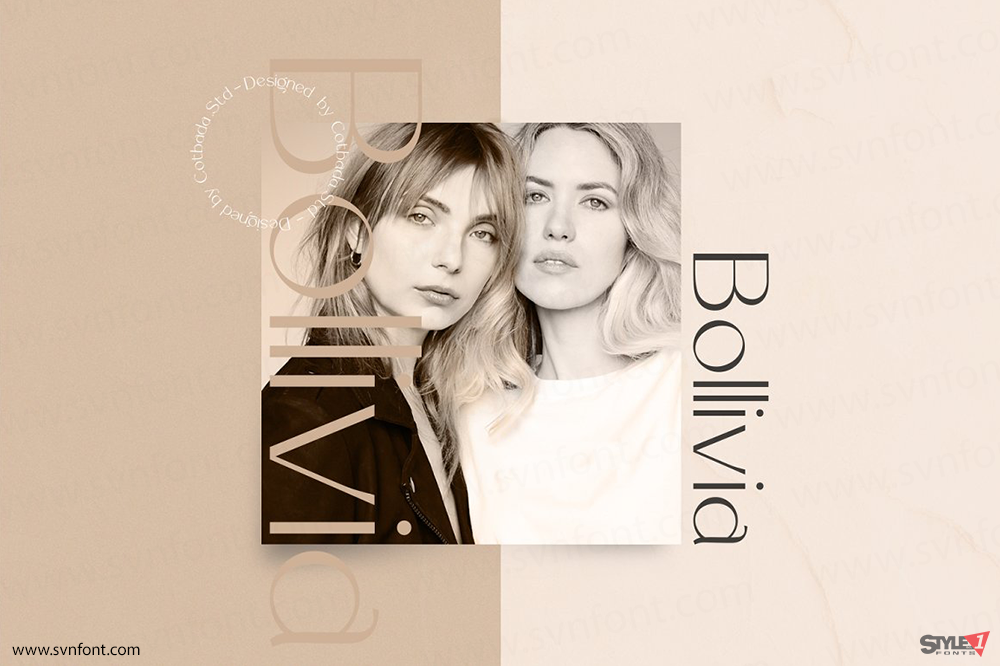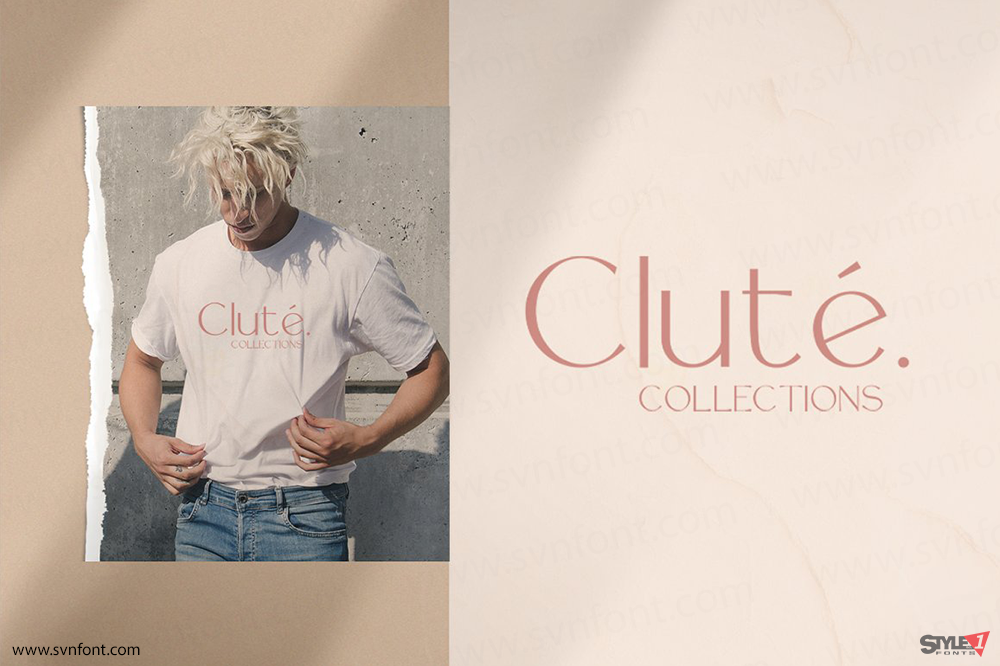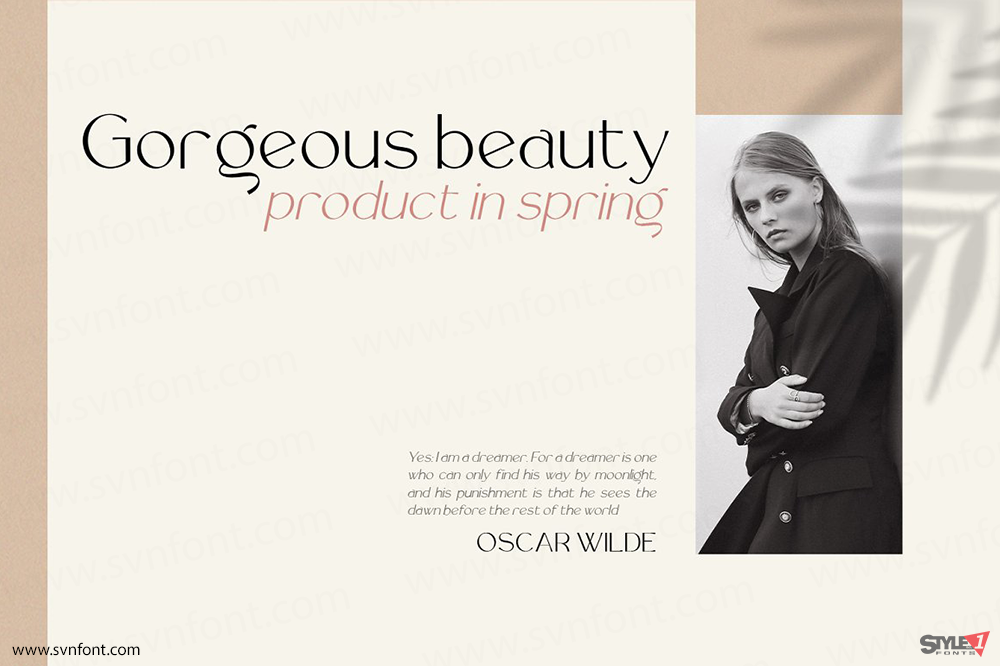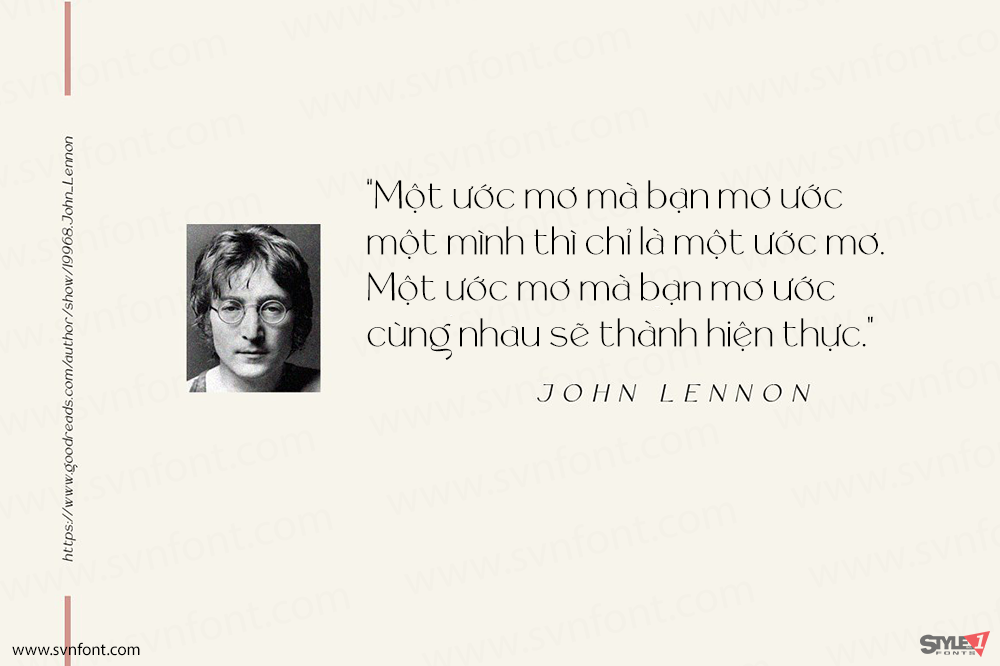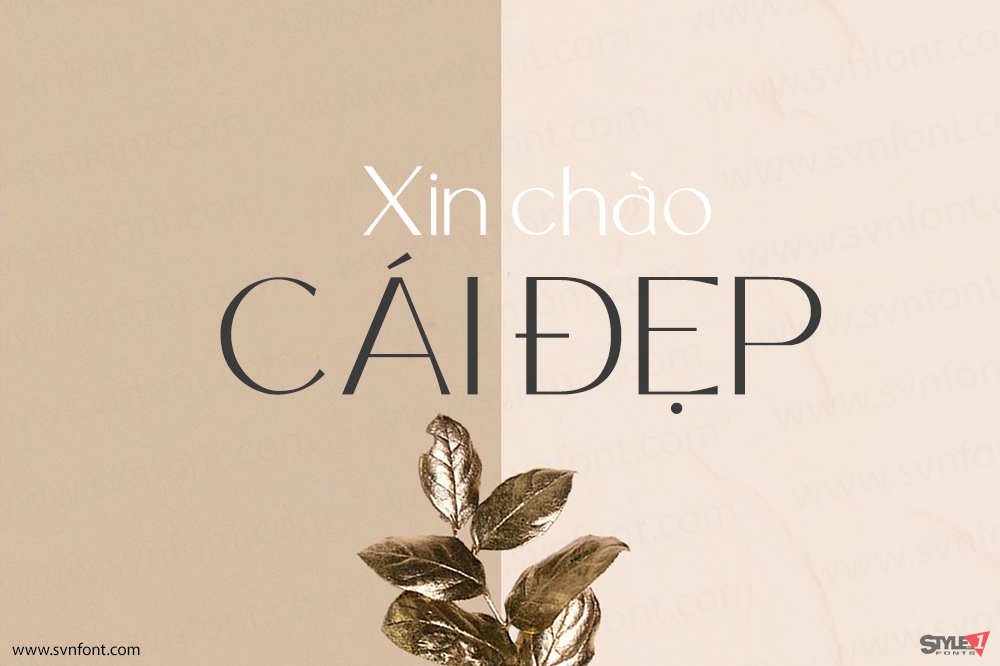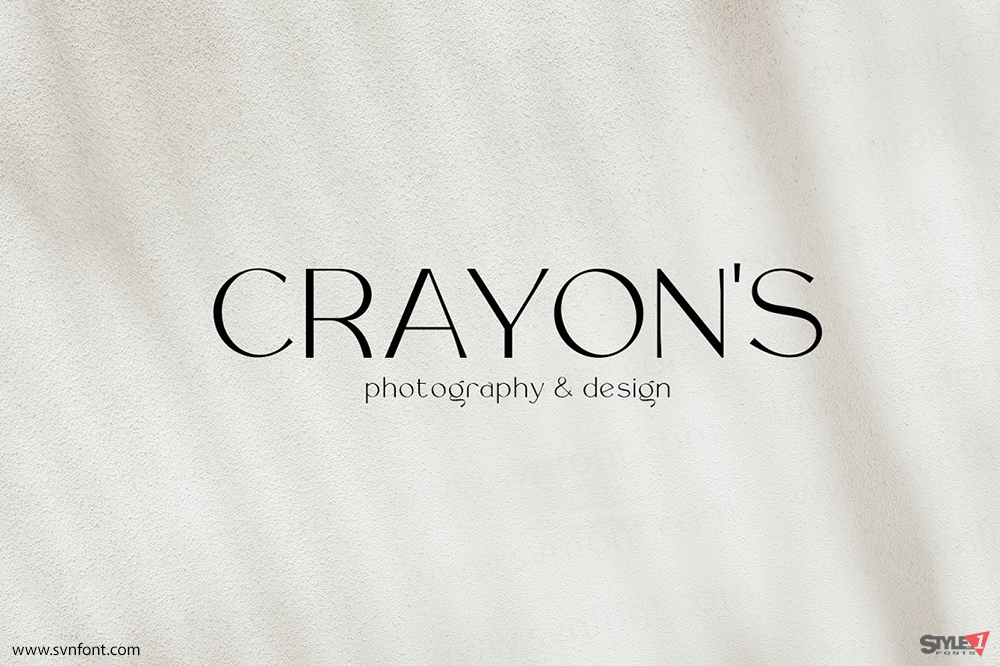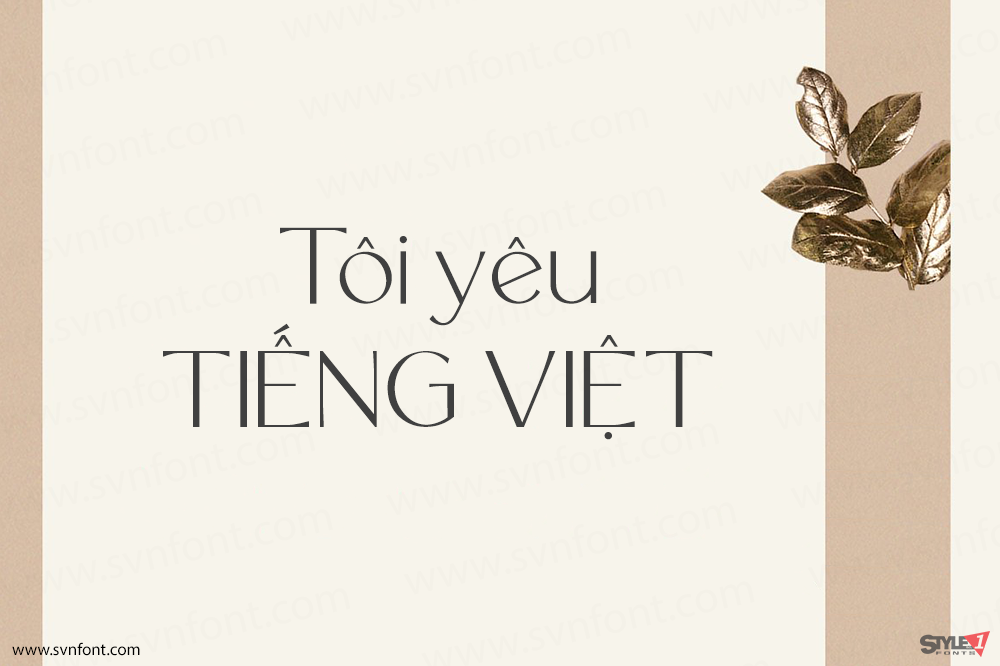
Rollgates Luxury là một typeface sans-serif sang trọng, vừa mang vẻ cổ điển thanh lịch vừa đậm chất hiện đại. Font rất phù hợp để tạo thiệp cưới tinh tế, dàn trang tạp chí, PowerPoint cao cấp, hoặc bất kỳ thiết kế đồ họa nào cần một diện mạo gọn gàng, sang trọng pha chút hơi hướng vintage.
Hãy tạo nên những thiết kế thật đẹp và đẳng cấp cùng Rollgates Luxury.
Nhà thiết kế: Cotbada Studio
Nhà phát hành: Cotbada Studio